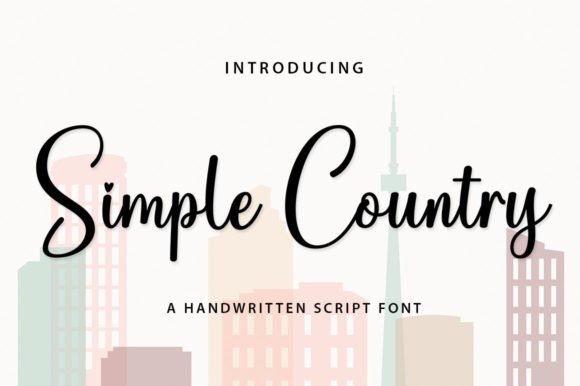
Simple Country
Se você está procurando por uma fonte que transmita elegância e sofisticação, o Simple Country é a escolha perfeita! Esta fonte foi especialmente criada para aqueles que buscam um visual fresco e refinado em seus projetos.
Características da Fonte Simple Country
O Simple Country é uma fonte rústica delicada que exibe uma elegância incomparável. Com sua forma suave e elegante, esta fonte se destaca em qualquer projeto que for utilizada. Com apenas algumas linhas elegantes, a fonte Simple Country consegue comunicar uma mensagem de sofisticação e elegância, tornando-a ideal para projetos de luxo, eventos sociais e muito mais.
Vantagens da Fonte Simple Country
- Visual Fresco e Refinado: A fonte Simple Country é projetada para trazer um ar fresco em seus projetos, tornando-os mais atraentes e interessantes.
- Elegância e Sofisticação: A forma suave e elegante da fonte Simple Country transmite uma mensagem de elegância e sofisticação, tornando-a ideal para projetos de luxo e eventos sociais.
- Fácil de Ler: Com sua forma simples e elegante, a fonte Simple Country é fácil de ler e entender, tornando-a ideal para projetos que precisam transmitir uma mensagem clara e concisa.
Como Usar a Fonte Simple Country
A fonte Simple Country é uma escolha perfeita para projetos que buscam transmitir elegância e sofisticação. Alguns exemplos de como usar a fonte incluem:
- Projetos de luxo, como catálogos de moda e revistas de alta qualidade
- Eventos sociais, como convites e cartões de agradecimento
- Páginas da web e aplicativos que buscam transmitir uma mensagem de elegância e sofisticação
O Simple Country é uma fonte rústica delicada que exibe uma elegância incomparável. Com sua forma suave e elegante, esta fonte se destaca em qualquer projeto que for utilizada. Se você está procurando por uma fonte que transmita elegância e sofisticação, o Simple Country é a escolha perfeita!